DynaSmart Tは、ダイナフォントTrueTypeフォントWin版、Mac版書体をした年間ライセンス。
UDフォントやグッドデザイン賞受賞書体「古籍書体」も収録され、収録される日本語書体全書体に新元号「令和」の合字に対応。また、星座仮名フォントやアートフォントなど楽しい特典フォント2,400書体以上も収録。
「DynaSmart T」はビジネス資料作成にも適した読みやすい「UDフォント」を収録
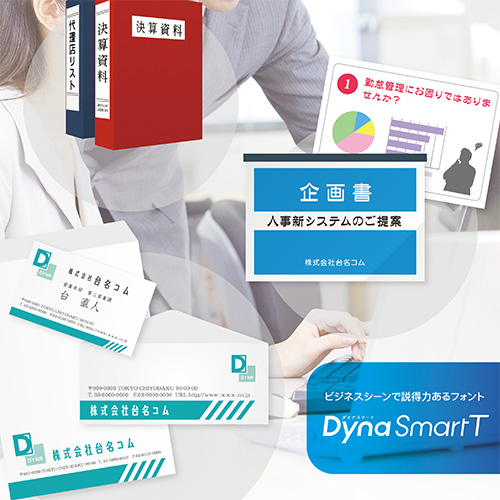
「DynaSmart T」には、誰にでも読みやすいフォントとして設計されたUDフォントを含む、複数の太さを持つ明朝体、ゴシック体、丸ゴシック体など基本書体を収録。
マイクロソフトの「Office」で作成するビジネス資料などで使用でき、読みやすいUDフォントや強調したい場面にオススメの極太フォントを駆使して説得力あるビジネス資料を作成することもできる。
年賀状や暑中見舞いなどプライベートシーンでは、収録されている楷書体、行書体、隷書体など豊富な毛筆系書体の使用がオススメ。
「DynaSmart T」は色々なデザインフォントでブランディングできる
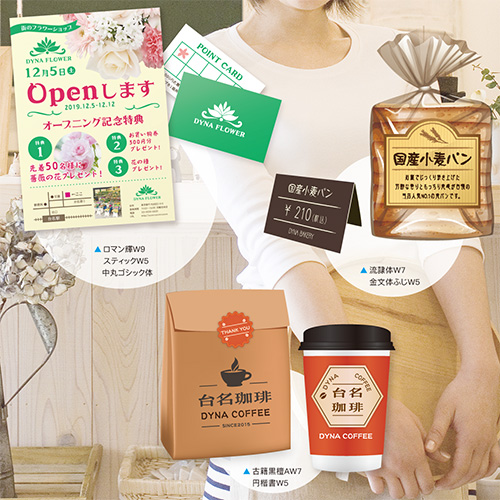
「DynaSmart T」はグッドデザイン賞受賞「古籍五書体」や「UDフォント」を収録
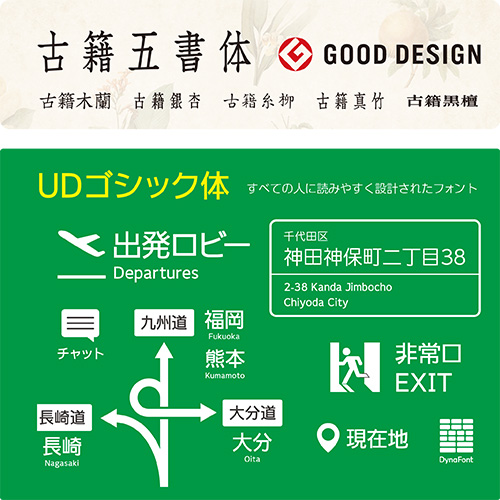
「DynaSmart T」は日本語書体が新元号「令和」の合字に対応
ダイナフォント年間ライセンス「DynaSmart T」に「雅風隷書体」「金文ゴシック体」が2019年5月28日に追加
DynaSmart Tに「雅風隷書体」「金文ゴシック体」の2書体が2019年5月28日に追加された。
「雅風隷書体」は、DF隷書体をベースにした隷書で、モダン・ライト・シンプルといったデザインエレメントを取り入れ書体。
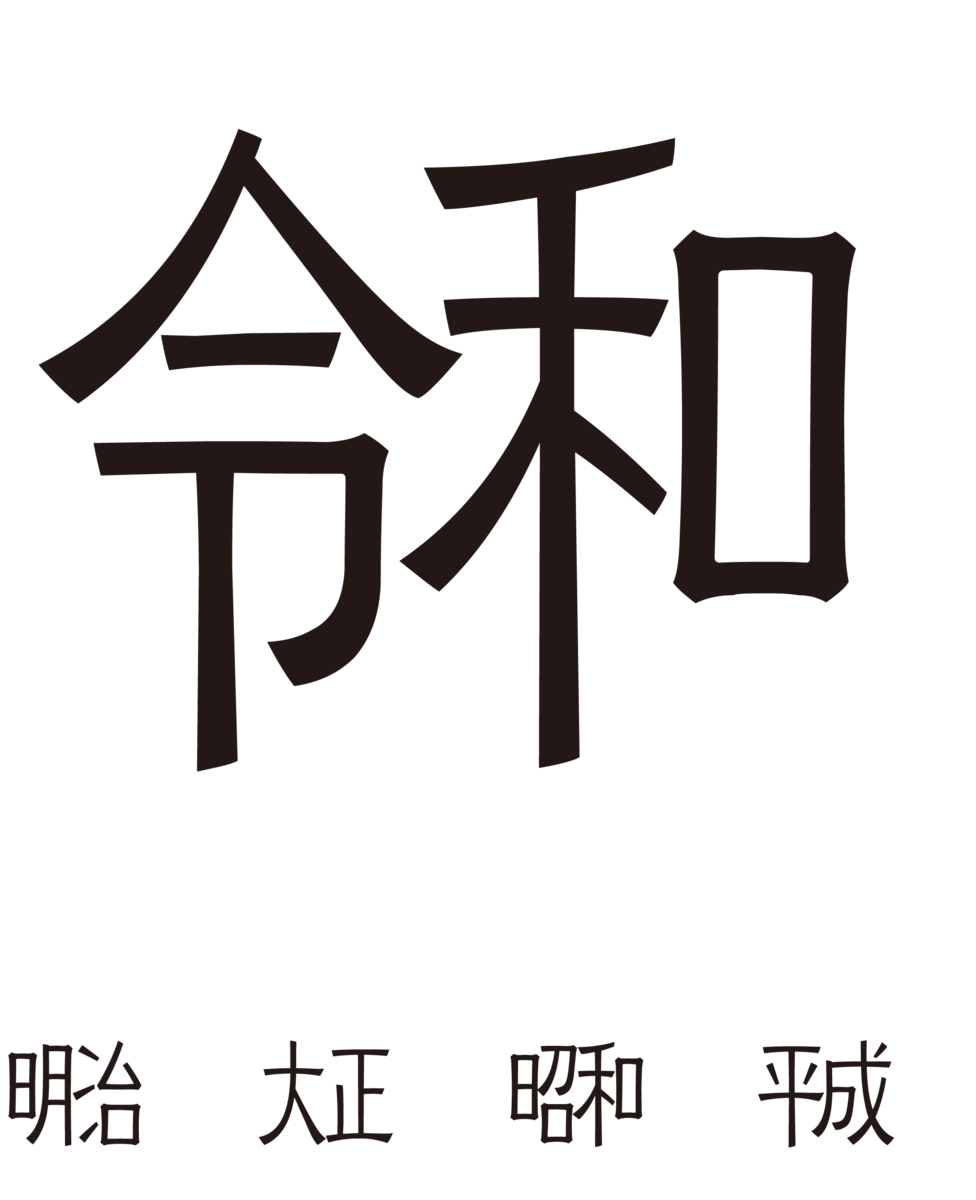
「金文ゴシック体」は、「金文体」をベースに、ゴシック体の角張りや太さの均一性といった特徴をブレンドした書体になっている。
「雅風隷書体」「金文ゴシック体」の2書体ともに新元号「令和」の合字も使用できる。